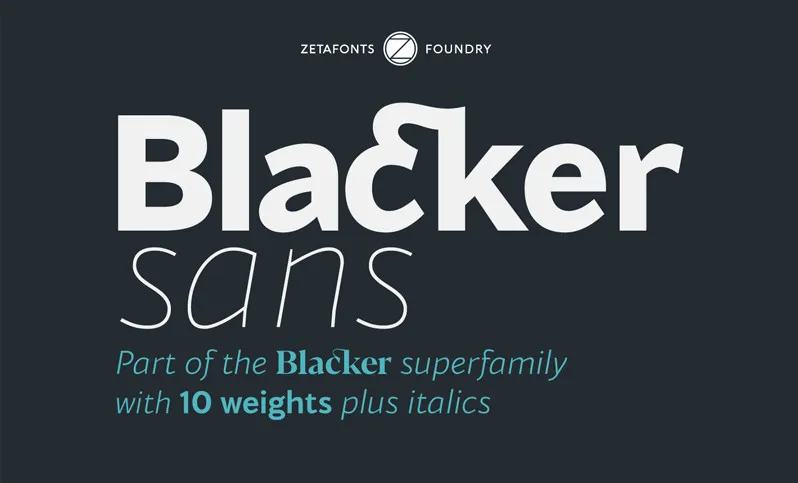
Descubra a novidade no mundo das fontes serifadas, com a introdução do famoso Blacker Sans Font Family pela Befonts. Desenhada por Cosimo Lorenzo Pancini e Andrea Tartarelli e compartilhada pela Zetafonts, essa nova família de fontes sans-serif é perfeita para projetos complexos em branding e editorial. Nasceu para combinar com outros tipos de uma maneira perfeita, Blacker Sans mantém seu tom sombrio e elegante sem perder a sua personalidade. O designer não apenas estendeu o peso da família à extremamente fina e pesada, mas também ao médio, permitindo uma grande versatilidade em uso para exibições. O tipo deixa os contrastes reduzidos até proporções grotescas, utilizando correções ópticas e detalhes cuidadosos na designação para expressar o espírito da família. O resultado é um poderoso trabalho-horse de fonte que preserva as características icônicas do Blacker: a forma hook dos caracteres minúsculos “f”, que se afina nas letras “a”, “c” e “e”. Além disso, os antigos traços espinhosos da família aparecem na forma dos “n”, “m”, “r” e “P”. Esta fonte sans-serif é perfeita para quem busca uma maneira elegante de destacar seus projetos. Com Blacker Sans Font Family, você terá a liberdade de escolher entre várias opções de peso sem perder o característico estilo do Blacker.